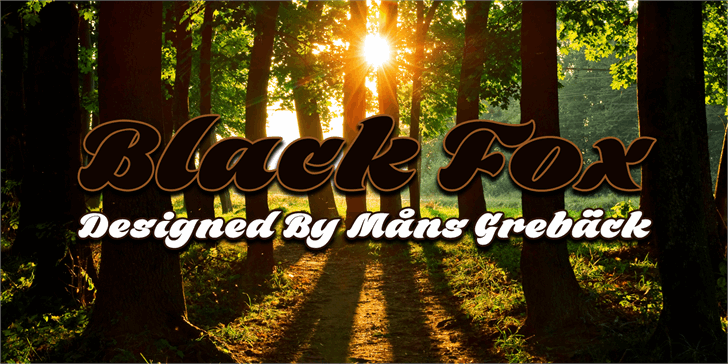
Black Fox font
A Black Fox é uma script-font que oferece uma escrita fluida e envolvente, perfeita para aqueles buscando um estilo elegante em suas criações. Criada pelo designer Hamilton, essa fonte traz a sensação de seriedade e sofisticação necessárias para trabalhos profissionais, ao mesmo tempo que oferece um toque suave e delicado ideal para projetos pessoais ou pequenas marcas. Com linhas elegantes e curvas suaves, a Black Fox não apenas proporciona um texto fácil de ler, mas também uma impressão visual única. Esta é uma opção perfeita para anúncios, logotipos e outros elementos visuais que precisam ser mais elaborados sem perder a clareza do texto. Através da Black Fox, Hamilton nos dá a oportunidade de incorporar um elemento único à nossa identidade visual, tornando cada projeto uma experiência diferenciada. Descubra por si mesmo como essa font pode transformar sua escrita em algo ainda mais especial com apenas alguns cliques. Visite o site do designer para adquirir uma licença comercial desta incrível fonte.